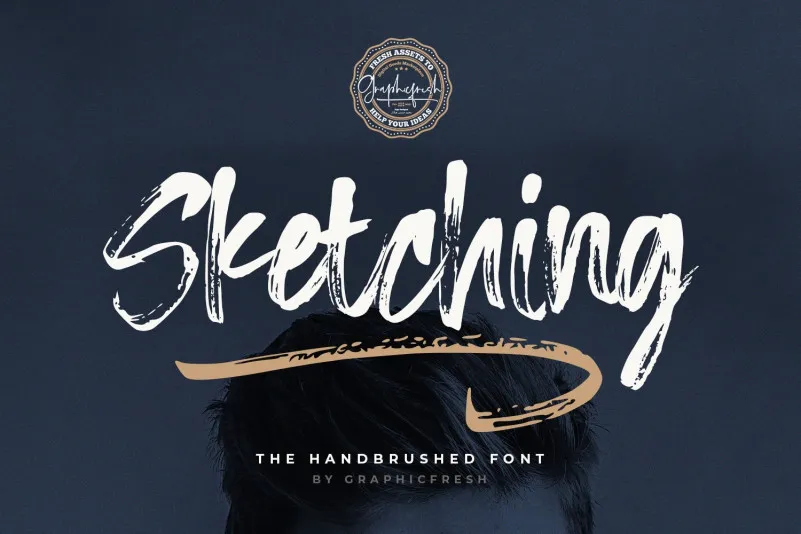
Sketching Font é uma tipografia criada à mão que combina um suave charme retrô com um toque moderno. Desenhado por Graphicfresh, essa fonte tem textura detalhada de esfera sequin, perfeitamente adaptável para diversos projetos, desde o estilo urbano até as marcas clássicas. Ideal para uso em identidade empresarial, como Instagram Quotes e cabeçalhos de blogs, também se adequa a moda, roupas e produtos de escritório, além de muito mais. Com seu conjunto alternativo de caracteres swash completo, você pode transformar completamente o visual do seu design. Sketching Font é perfeito para designers em busca de um estilo único e versátil que se adapta a qualquer projeto.